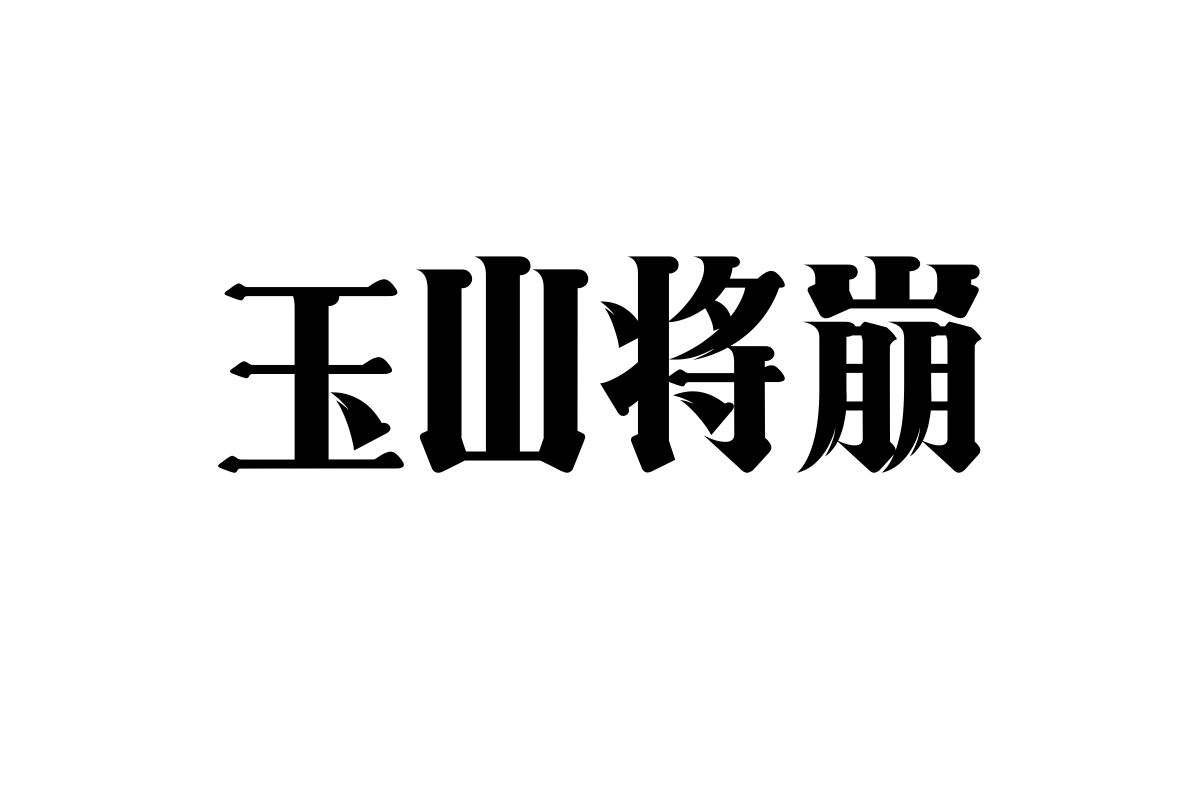
惊鸿体是一种书法字体,其特点是字形优美、线条流畅,给人以优雅、灵动的感觉。这种字体在古代文人墨客的作品中常见,如唐代诗人杜甫的《春望》等。
惊鸿体的特点是笔画粗细变化较大,既有粗犷的线条,又有细腻的笔触,使得整个字体既有力度又有韵味。此外,惊鸿体的笔画转折处往往有顿挫之感,增加了字体的节奏感和动感。
惊鸿体的结构紧凑,字形紧凑而不拥挤,给人一种舒展的感觉。同时,惊鸿体的字间距也较为宽松,使得整个作品显得更加和谐、自然。
总的来说,惊鸿体是一种具有独特美感和艺术价值的书法字体,深受人们喜爱。